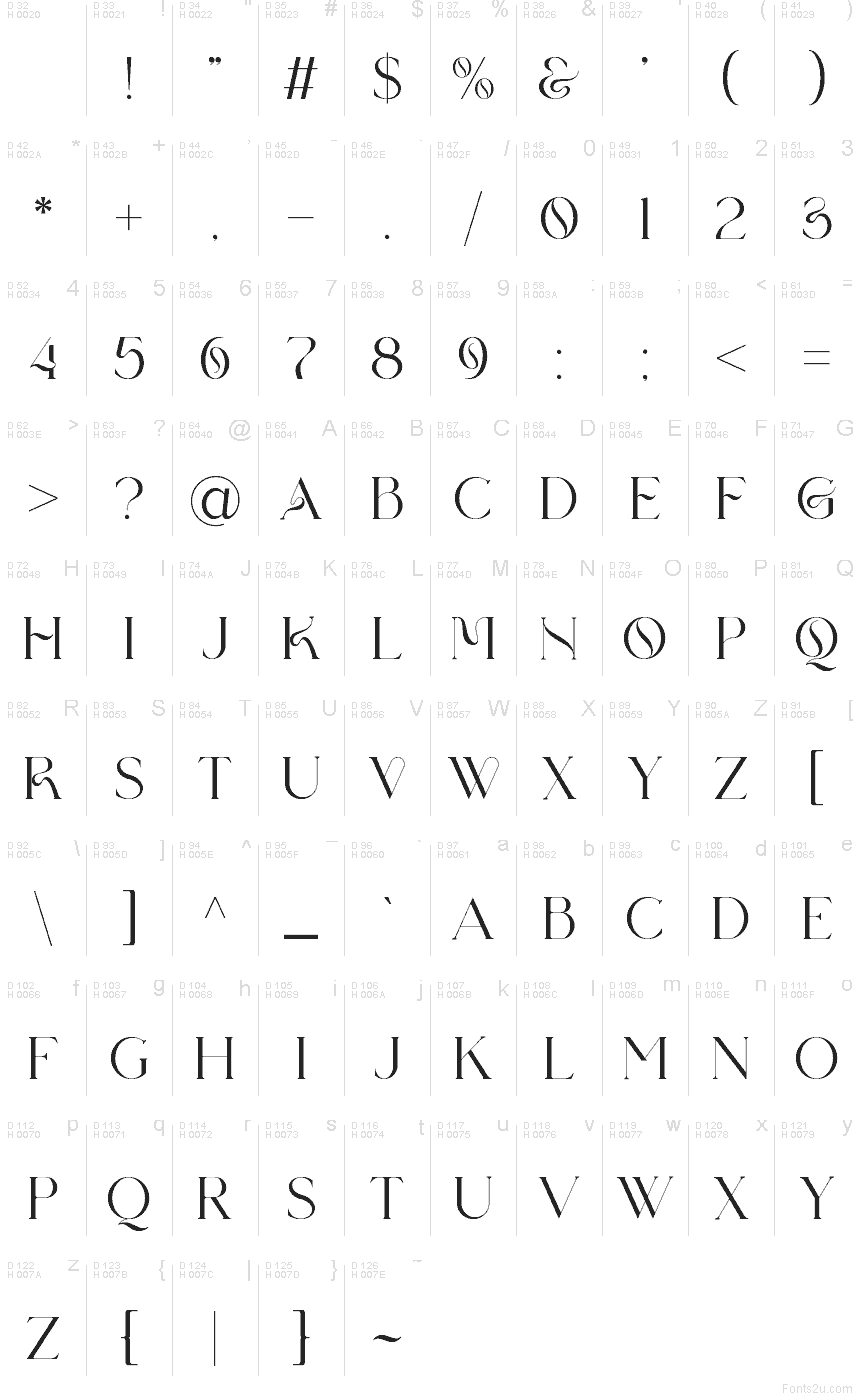
Minneth, autorstwa Ermedia Studio, to darmowy font retro typu display o wyrafinowanym, redakcyjnym charakterze w stylu Art Nouveau. Wysokie, kontrastowe litery łączą w sobie wyraźną szeryfową strukturę z pełnymi wdzięku, kolistymi detalami, co nadaje krojowi elegancki, dekoracyjny rytm.
Ten darmowy font świetnie sprawdzi się w nagłówkach magazynów modowych, na opakowaniach perfum, szyldach butików, papeterii ślubnej czy w krótkich hasłach, gdzie elegancka typografia dominuje w projekcie. Znakomicie prezentuje się także na planszach tytułowych, zwłaszcza gdy pożądany jest powściągliwy klimat vintage.